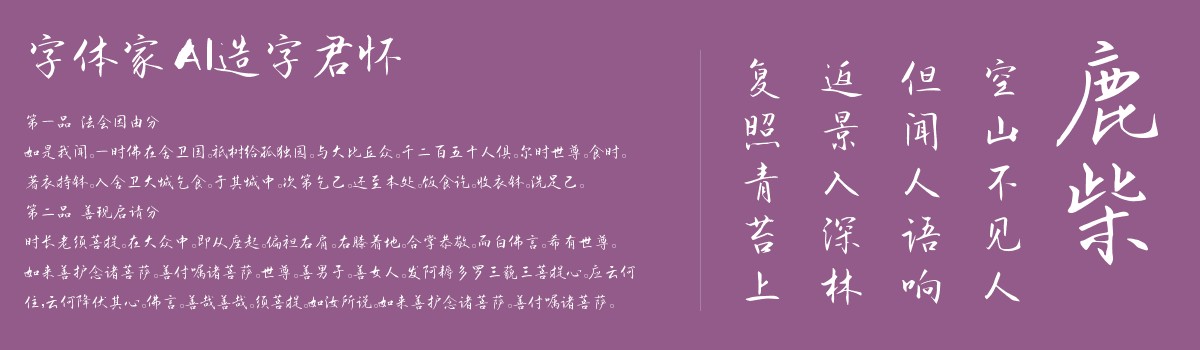
字体家AI造字君怀
字体家AI造字君怀是一款由字体家AI神笔造字生成的一款艺术字体,这款字体似毛笔手写,线条有自然粗细变化:起笔常带轻顿,如指尖轻按纸面;收笔或轻提如发丝,或渐粗似蓄力。转折处多圆转,像水流绕过石墩般柔和,无生硬棱角。笔画间偶有细劲牵丝,似书写时笔尖自然牵连,连贯不拖沓。整体结构舒展却重心沉稳,粗笔画如磐石扎实,细笔画似柳叶飘逸,力度对比藏着书写韵律,像人从容挥毫,既有手写的温度,又有书法的雅致法度。。比较适合用于艺术类装饰文字,海报、网页、广告设计,室内装饰,平面标题设计、食品包装、品牌标志等。